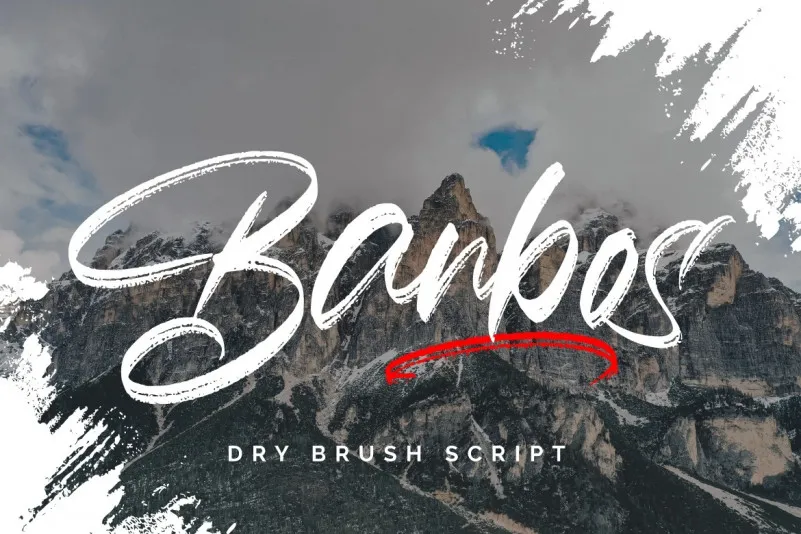
Banbos Brush Font – Download Grátis
A Banbos Brush Font é uma elegante escolha para quem procura um estilo handwritten com toques bruscos e deslavado. Com traços robustos, inclinações marcantes e um forte carácter próprio, essa fonte torna seu design mais atraente e poderoso. Ideal para uso em criações como logomarcas, frases inspiradoras ou qualquer outro tipo de projeto visual, esta Banbos Brush Font é uma excelente adição ao seu arsenal de recursos gráficos. Sua textura única e personalidade forte garantem que sua marca fique marcada na memória do público. Que tal incorporar um toque autêntico e poderoso a seu trabalho com esta fonte?